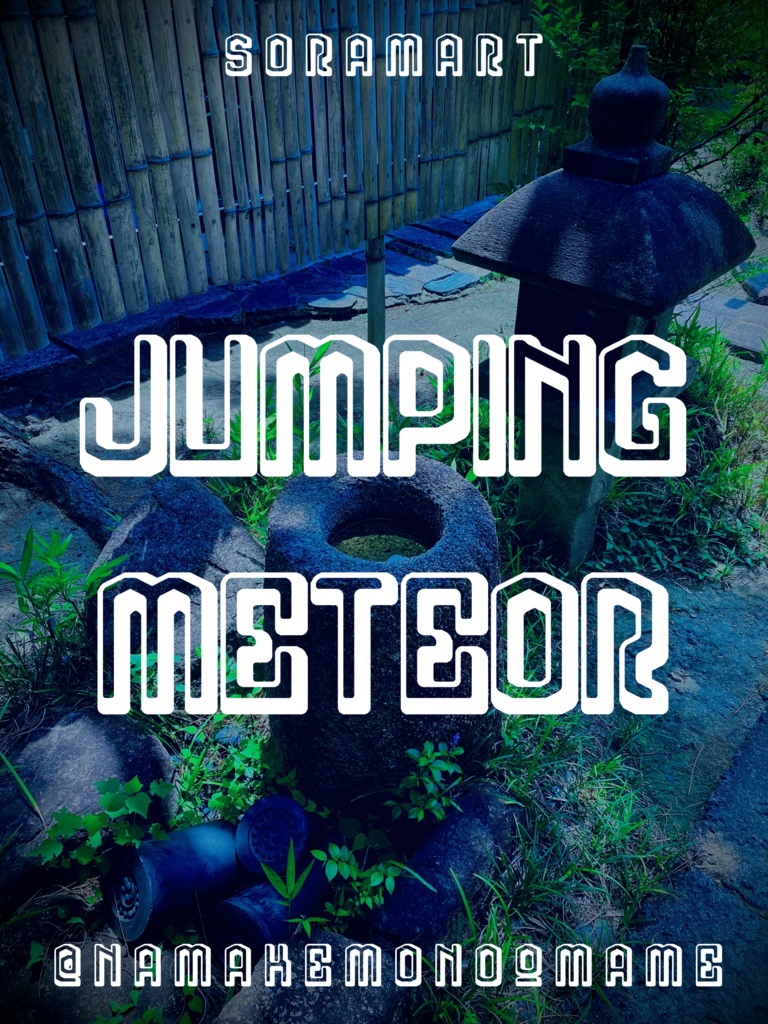
そらマートフォントデータ”Jumping Meteor”ダウンロード商品¥ 2,500カートに入れるギフトとして贈る「ギフトとして贈る」とはゲーミングポップな白抜きフォント "Jumping Meteor" です。 「TrueTypeフォントファイル」という形式です。 ダウンロードした後、Zipファイル内のデータをインストールしてお使いください。 このフォントは商用利用可となっております。 お客様の制作・創作活動のお役に立てれば幸いです。 ※使用上の注意事項などは、添付のReadmeをお読みください。そらマートFANBOX開設中フォント・書体フォントデータ”Tonik Crate”そらマート¥ 0フォント・書体フォントデータ”Vapor Sprout Edge”そらマート¥ 2,500フォント・書体フォントデータ”Vapor Sprout Wide”そらマート¥ 2,500フォント・書体フォントデータ”Vapor Sprout”そらマート¥ 2,500フォント・書体フォントデータ”Star Shoot Ray”そらマート¥ 2,500フォント・書体フォントデータ”Star Shoot Black Wide”そらマート¥ 2,500フォント・書体フォントデータ”Star Shoot Black”そらマート¥ 2,500フォント・書体フォントデータ”Mars Invader Balloon”そらマート¥ 2,500フォント・書体フォントデータ”Mars Invader Wide”そらマート¥ 2,500フォント・書体フォントデータ”Mars Invader”そらマート¥ 2,500フォント・書体フォントデータ”Rock Cut Serif”そらマート¥ 2,500フォント・書体フォントデータ”Rock Cut Drop Wide”そらマート¥ 2,500フォント・書体フォントデータ”Rock Cut Drop”そらマート¥ 2,500フォント・書体フォントデータ”Longtail Sans Serif Slashed”そらマート¥ 2,500フォント・書体フォントデータ”Longtail Sans Serif Bold”そらマート¥ 2,500フォント・書体フォントデータ”Longtail Sans Serif”そらマート¥ 2,500フォント・書体フォントデータ”Pretty Commando”そらマート¥ 2,500フォント・書体フォントデータ”Abyss Dive Punk Retro”そらマート¥ 2,500フォント・書体フォントデータ”Abyss Dive Punk Wide”そらマート¥ 2,500フォント・書体フォントデータ”Abyss Dive Punk”そらマート¥ 2,500もっと見る